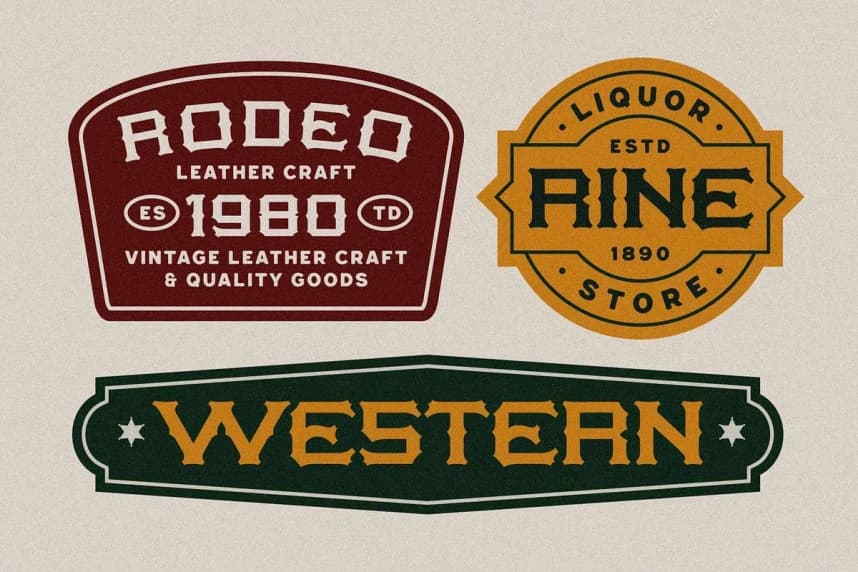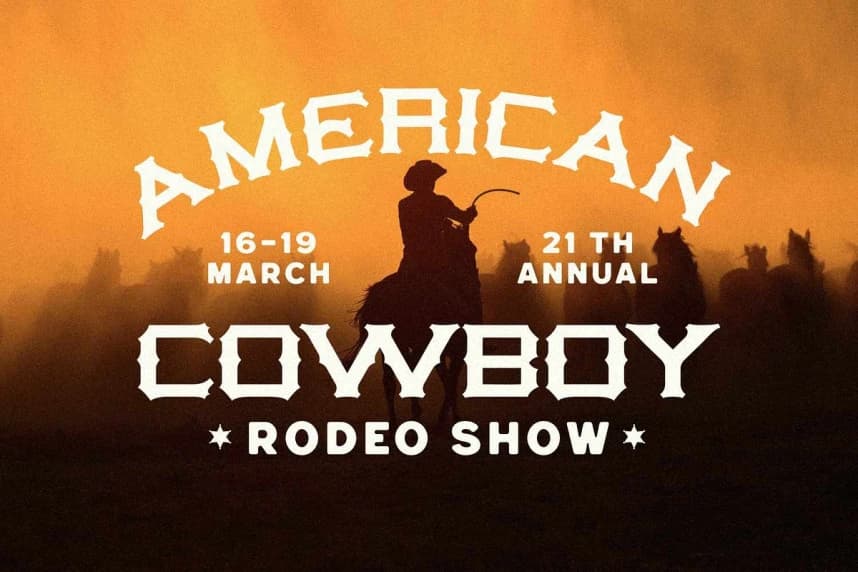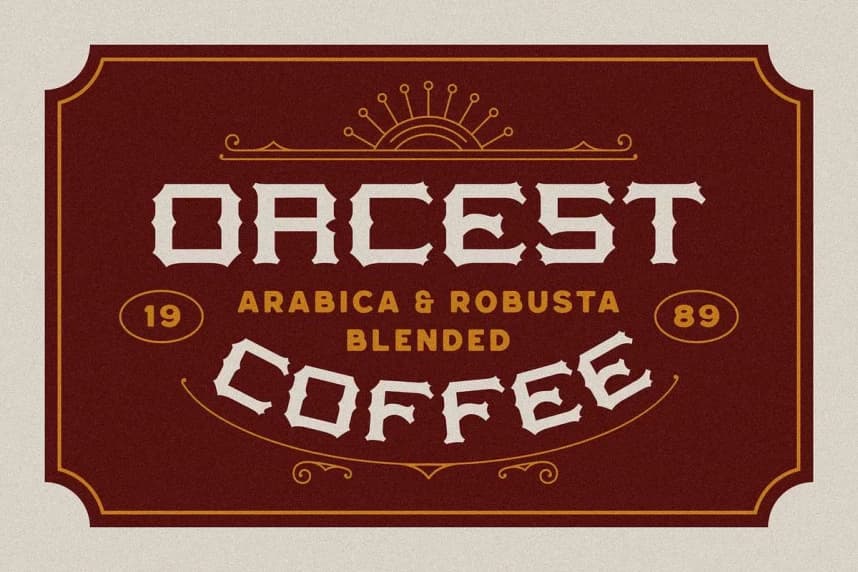
Henir Vintage Font
Henir Vintage Font, tasarımlarınıza Amerikan Batısı'nın sert çekiciliğini getiren vintage bir western fontudur. Oyulmuş harf biçimleri ve keskin, blok benzeri serifleri eski rodeo afişlerinin, sığır çiftliği damga demirlerinin ve sınır kasabasındaki saloon tabelalarının kararlılığını yansıtır.
Henir Vintage Font, tasarımlarınıza Amerikan Batısı'nın sert cazibesini getiren vintage bir Western yazı tipidir. Onun oyulmuş harf biçimleri ve keskin, slab benzeri serifler, eski rodeo afişlerinin, sığır çiftliği damga demirlerinin ve sınır bölgelerindeki saloon tabelalarının sertliğini yansıtır.